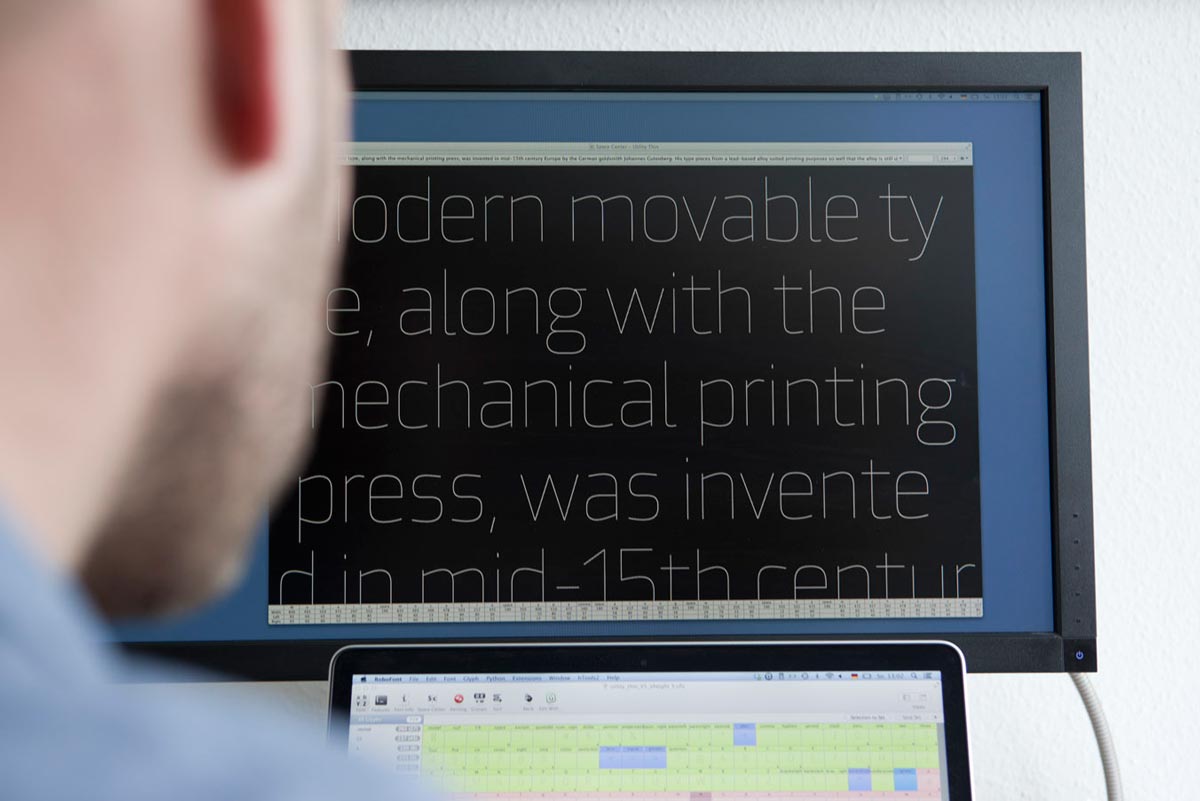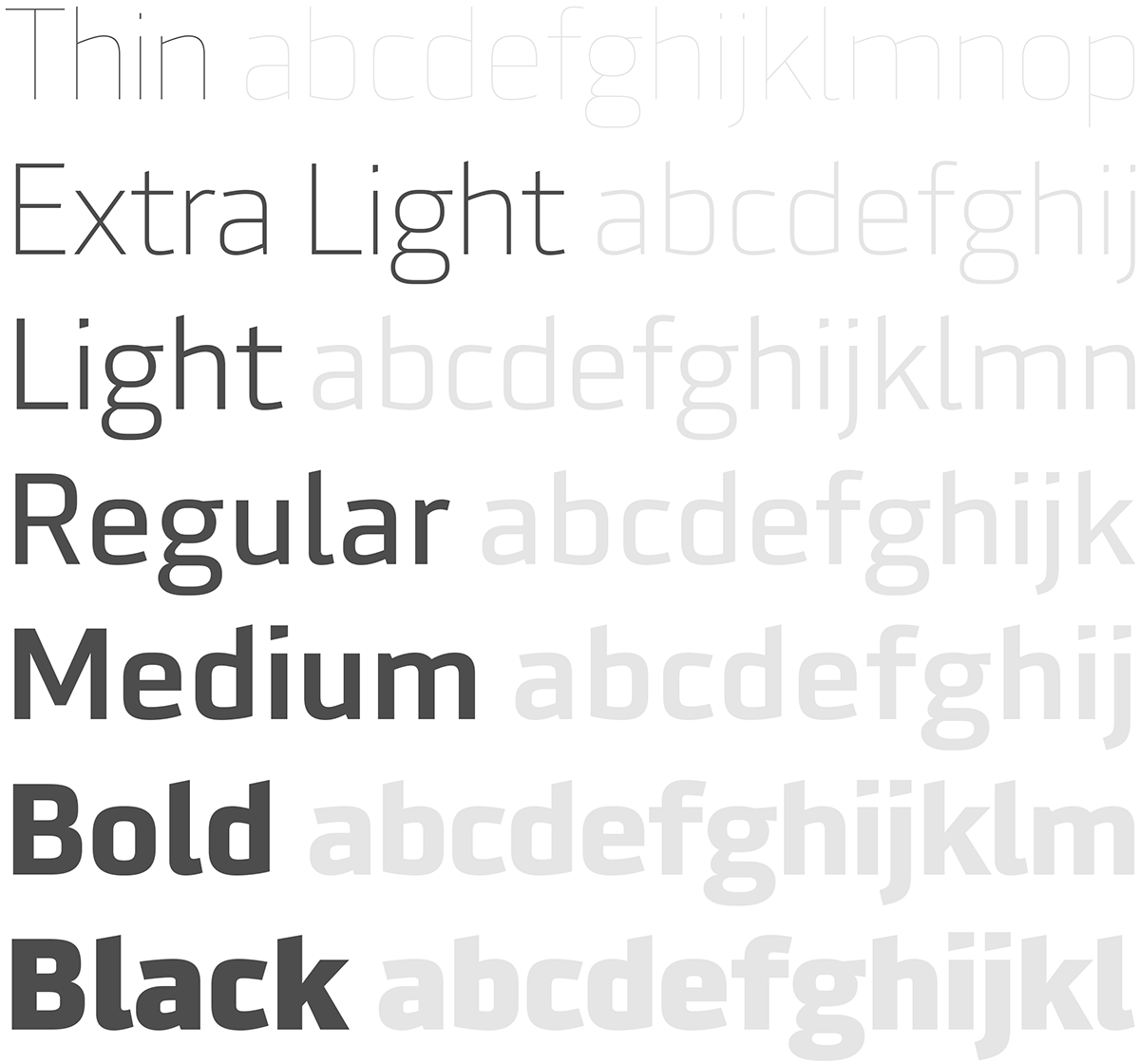
Neue Berliner Foundry: Mauve Type
Die ohnehin lebendige Font-Szene in Berlin ist um eine Foundry reicher: Mauve Type ist ein unabhängiger Kleinverlag, der sich auf hochwertige Display-Schriften spezialisiert.
Mauve-Fonts wirken dort, wo Display Typografie zum Einsatz kommt. Je größer, desto besser. Gründer Eike Dingler studierte Schrift-Design in Den Haag und Grafik-Design in Düsseldorf und Arnhem. Er arbeitete mit Peter Bil’ak bei Typotheque und betreibt nebem dem Schriftenentwurf ein Grafik-Design-Büro.
Mit Mauve Type erforscht Eike die visuellen und konzeptionellen Möglichkeiten von Display- und Headline-Schriften. Schriften, die in großen Größen das Auge einfangen, können Grafikdesignern das Leben deutlich vereinfachen. „Sie machen einfach mehr Spaß bei der Arbeit, sparen viel Zeit und sorgen für bessere Ergebnisse.“, so Eike.
Seine erste Veröffentlichung und Anlass für die Foundry Gründung ist Eikes Aufsehen erregender Versuch, die schwindelerregend wie inspirierende Menge an Details der mittelalterlichen Handschrift-Initialen einzufangen in eine zeitgemäße Form zu überführen.
Das Pattern Project ist eine ornamentale und gleichzeitig hochmoderne Display-Familie mit neun Fonts, die auf auf Rechtecken, Rauten und Dreiecken beruhen. Dabei entstand kein Buchstabe mit der Hand. Vielmehr entwickelte Eike die Formen der Glyphen aus einer Datenbank mit Vierecken und Kreisteilen und „füllte“ die Muster, per Pattern App, in die Formen. Neben den Schriften kann auch die App erworben werden und gestattet es, jedes erdenkliche Muster in Buchstabenformen zu füllen.Wer sich sofort in die Mailing Liste von Mauve Type einträgt, erhält 25% Rabatt.
Über Details zu Konzept und Entwicklung des Pattern Projects informiert dieser Kurzfilm:
Shutterstock: Die visuellen Trends 2015
Unscharfe Hintergründe, lineare Grafiken und überraschende Blickwinkel: Diese drei Trends bestimmen das Design und die visuelle Gestaltung weltweit. In Deutschland sind vor allem Bilder im Instagram-Stil sowie Infografiken gefragt. Der boomenden Technologiebranche hierzulande ist es vermutlich zu verdanken, dass die Nachfrage nach Start-up-Bildern enorm gestiegen ist.
Das sind nur einige der Designtrends 2015, die der weltweit aktive Medien-Anbieter Shutterstock auch in diesem Jahr wieder mit einer interaktiven Infografik beleuchtet (Fontblog berichtete vor einem Jahr über die grafischen Tends 2014). Die neue Erhebung umfasst nicht nur die visuellen Trends 2015 im Bereich Bild, sondern auch Video, Musik sowie Social Media. Diese Erweiterung spiegelt das Portfolio von Shutterstock wider, das ursprünglich als Bildagentur gestartet war und heute auch Footage und pauschal lizenzierte Musik anbietet. Die aktuellen Erkenntnisse basieren natürlich wieder auf der Analyse der Kunden-Downloads und -Suchanfragen aus 2014.
Lokale Ereignisse und Trends beeinflussen die visuelle Sprache der Märkte weltweit (Quelle: Shutterstock)
Familienzuwachs: Lukas Schneider & FF Utility
Wie wirkt die Erweiterung einer Schriftfamilie sich auf das Gesamtkonzept aus? Sind Familien je ausgewachsen? FF Utility, 2002 als Diplomarbeitsprojekt begonnen, erhielt kürzlich zwei neue Light-Schnitte – und eine komplette Überarbeitung. Zu den Hintergründen haben wir mit Lukas Schneider gesprochen.
Eine Schrift zu gestalten war für Designer Lukas Schneider schon deshalb naheliegend, weil man während des Studiums „ständig mit Schrift hantiert“ – und er im Rahmen seiner Diplomarbeit kostbare sechs Monate Zeit hatte. Zudem fand Lukas („Das war wie eine Erleuchtung für mich!“) am Schwarzen Brett einen Aushang von Linotype: Akira Kobayashi suchte eine studentische Aushilfskraft („Ich hab den Zettel sofort abgerissen, damit ihn kein anderer sieht“). So profitierte Lukas von Supervision bei der Entwicklung der FF Utility – oder damals noch ihrer Urform namens Gazoline. Die lag nach dem Diplom allerdings „erstmal ewig rum“ …
FontFont veröffentlichte die Ur-FF-Utility-Familie mit fünf Fonts 2008. Im letzten Monat kamen die Erweiterungen Thin und Extra Light hinzu.
Wie die weitere Entwicklung der FF Utility verlief, beschreibt Lukas so:
Lukas, war der Name Programm?
Nicht ursprünglich. Beim Gestalten dachte ich an 50er-Jahre-Schriften an Tankstellen in den USA und hatte Gazoline im Sinn; das fand ich kraftvoll – ging aber nicht, gab es schon. Es gab Namensvorschläge von Stephen Coles (soweit ich mich erinnern kann), – Utility fand ich am passendsten. Irgendwann sieht man das pragmatisch. Zudem hatte sich die Ästhetik der Schrift im Gestaltungsprozess geändert.
Warum kommt jetzt die Erweiterung? Was war deine Motivation?
Die Erweiterung, oder die Idee zur Erweiterung, war schon da, bevor die FF Utility mit fünf Schnitten 2008 als FontFont herauskam.
Das klingt, als hätte FontFont gedrängelt?
Ja, schon (lacht leise)… Zum Beispiel möchte das FF-Type-Department immer vier Ziffernsätze. Die haben wir für fünf Ur-Schnitte gemacht von Light bis Black. Damals dachte ich schon, es wäre schön, etwas noch Leichteres für große Headlines zu haben. Oder eine Condensed. Schon 2008 habe ich erste Versuche gemacht – nebenher – dann lagen die Sachen eine Weile rum – und jetzt war es einfach an der Zeit.
Inzwischen konzentriere ich mich mehr auf Schrift (Lukas Schneider resümiert).
Der Wettbewerb »Die schönsten deutschen Bücher« geht zurück auf das Jahr 1929 und ist damit einer der ersten Wettbewerbe der Branche.